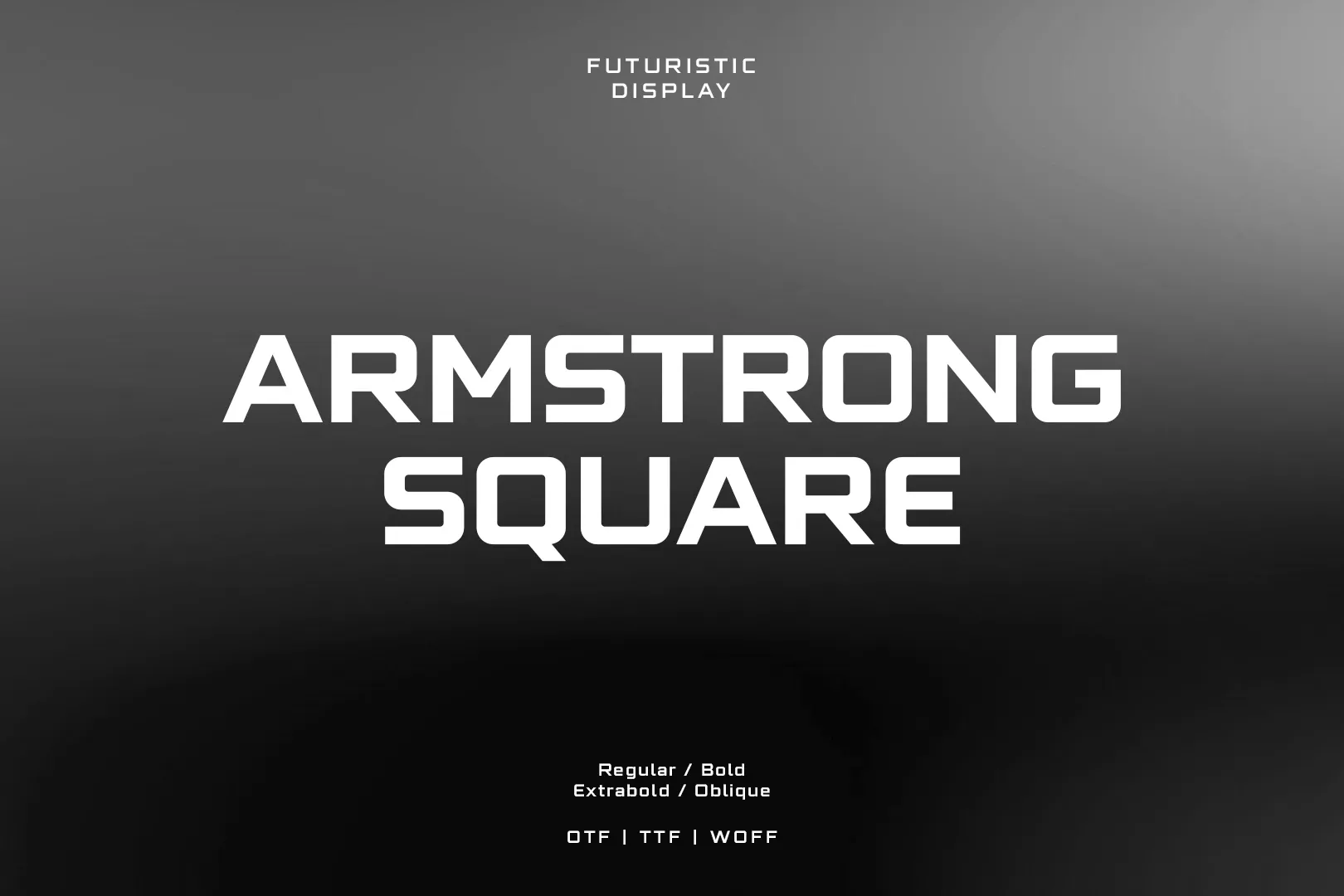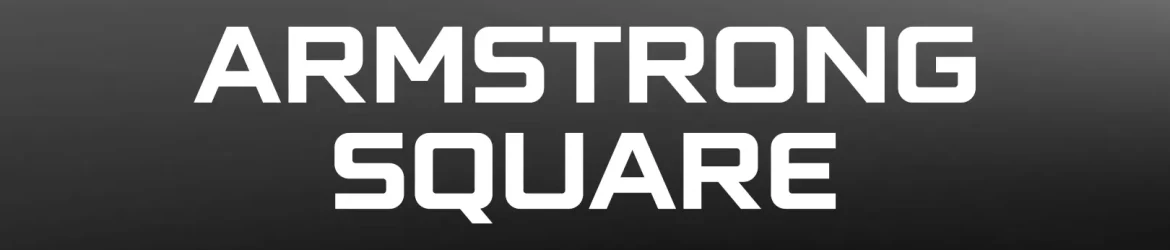
Esta fonte é uma forte yold sans-serif ideal para cabeçalhos web e logotipos. Ela foi criada pelo typologic e se destaca pela sua forma quadrada, que garante consistência visual sem ser excessivamente rígida. A Armstrong transmite um forte mensagem que a torna perfeita como texto de títulos ou subtítulos. O conjunto de três pesos fonte vem acompanhado da versão itálica e até mesmo caracteres alternativos para adaptar à sua necessidade específica. Este é o tipo certo para qualquer projeto que exija uma aparência moderna e poderosa, criando um impacto imediato tanto em ambientes digitais quanto em impressões físicas.